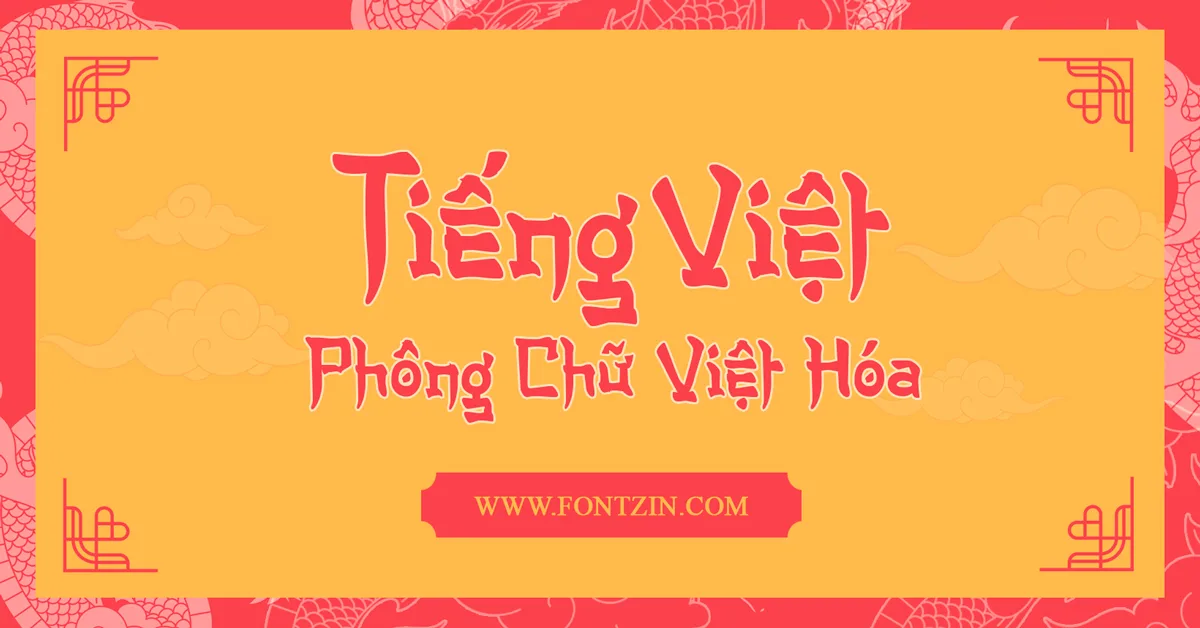
Fz CoTrang – Mang hơi thở cổ điển cho thiết kế hiện đại
Bạn đang tìm kiếm một font chữ mang đậm phong cách cổ trang để tạo nên những thiết kế độc đáo? Font Fz CoTrang chính là lựa chọn hoàn hảo dành cho bạn! Với thiết kế lấy cảm hứng từ các ký tự Hàn Quốc, font chữ này sở hữu nét đẹp tinh tế, cân đối, đậm chất Á Đông.
Giới thiệu font Fz CoTrang
• Thiết kế: Các ký tự được trau chuốt tỉ mỉ, tạo nên sự hài hòa và cân đối, mang đậm dấu ấn của thư pháp truyền thống.Ứng dụng:
1. Thiết kế đồ họa: Tạo điểm nhấn cho các poster, banner, logo với phong cách cổ điển.
2. In ấn: Làm nổi bật các ấn phẩm như thiệp cưới, danh thiếp, bao bì sản phẩm.
3. Truyền thông: Thiết kế các ấn phẩm quảng cáo, tờ rơi, brochure mang đậm tính nghệ thuật.
• Nguồn gốc: Font Fz CoTrang được FontZin Việt hóa dựa trên font gốc AnnyeongHaseyo, đảm bảo chất lượng và tính ổn định.
Đây là phiên bản chỉnh sửa và Việt hóa bởi FontZin nên được đổi tên font gốc thành Fz CoTrang.
Fz CoTrang có những điểm khác biệt so với font gốc như: Dấu được làm lại để phù hợp Tiếng Việt, các ký tự có nhiều họa tiết được vẽ lại nhằm giúp dễ đọc và phù hợp với bỏ dấu hơn, có thêm 1 bộ ký tự thường với chiều rộng hẹp hơn.